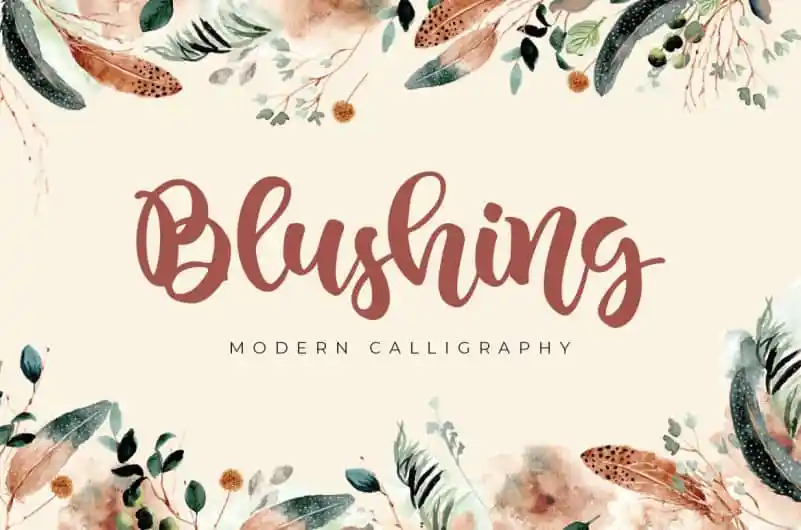
Blushing Script Font
A Blushing Script Font é uma elegante fonte escrita à mão que transmite sofisticação através dos traços elegantes das letras gregas ou romanas. Desenvolvida com cuidado para se destacar, ela mantém seu lado clássico da tipografia enquanto também adquire um toque contemporâneo e vibrante. Esta fonte é perfeita para aqueles que buscam uma abordagem mais criativa nas suas criações de design. Perfeitamente adaptável a diversos projetos, seja para gráficos ou ilustrações digitais, ela traz uma sensação de frescura e modernidade ao seu trabalho. Adote-a e transforme seus trabalhos em verdadeiros destaques.
Designer: agniardi